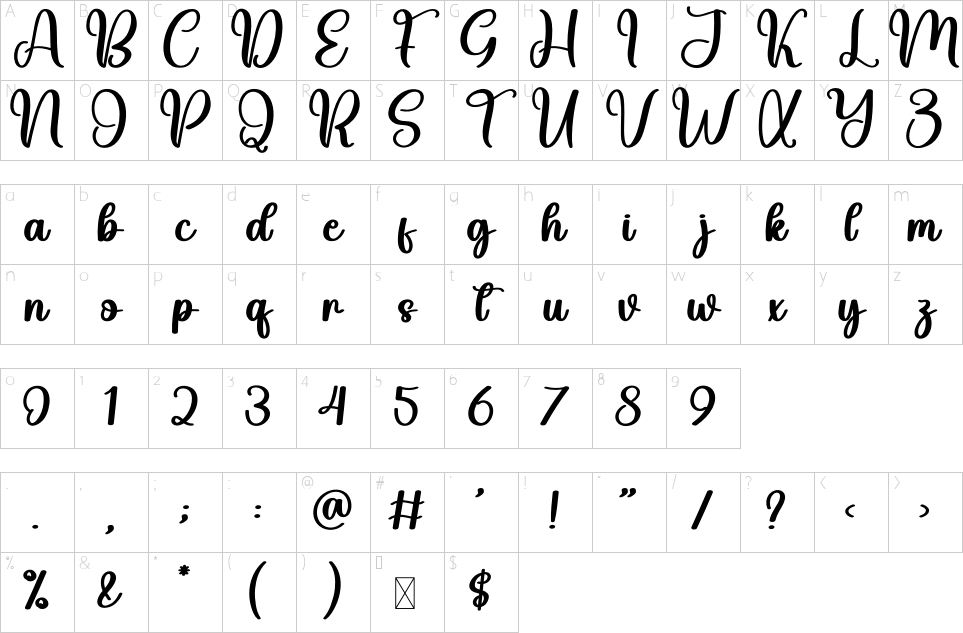
A fonte Grinch Wonderful oferece uma atmosfera animada e única para aqueles que buscam algo diferente no seu dia a dia. Desenvolvida pelo designer scratchones, esta fonte retrata um lado divertido de natal com suas letras desenhadas em estilo cartoon, dando vida às palavras mais vivas e coloridas do universo infantil. Esta fonte é ideal para criar cartazes de Natal ou qualquer tipo de design gráfico que seja o centro das atenções durante a época festiva, garantindo um toque irreverente e divertido ao seu trabalho. Com uma variedade de estilos disponíveis, Grinch Wonderful não apenas torna sua próxima tarefa de design mais fácil, mas também adiciona um toque especial de criatividade às suas criações. Completamente gratuita, esta fonte está disponível tanto para o sistema Windows quanto para Mac, permitindo a utilização em uma variedade de dispositivos. Com este design único e acessível, Grinch Wonderful é uma escolha ótima para aqueles que buscam diversificar seu portfolio de fontes com um elemento que chama a atenção imediatamente. O fato de ter sido baixado 561 vezes já reflete o quanto esta fonte está ganhando popularidade entre designers e criadores de conteúdo.